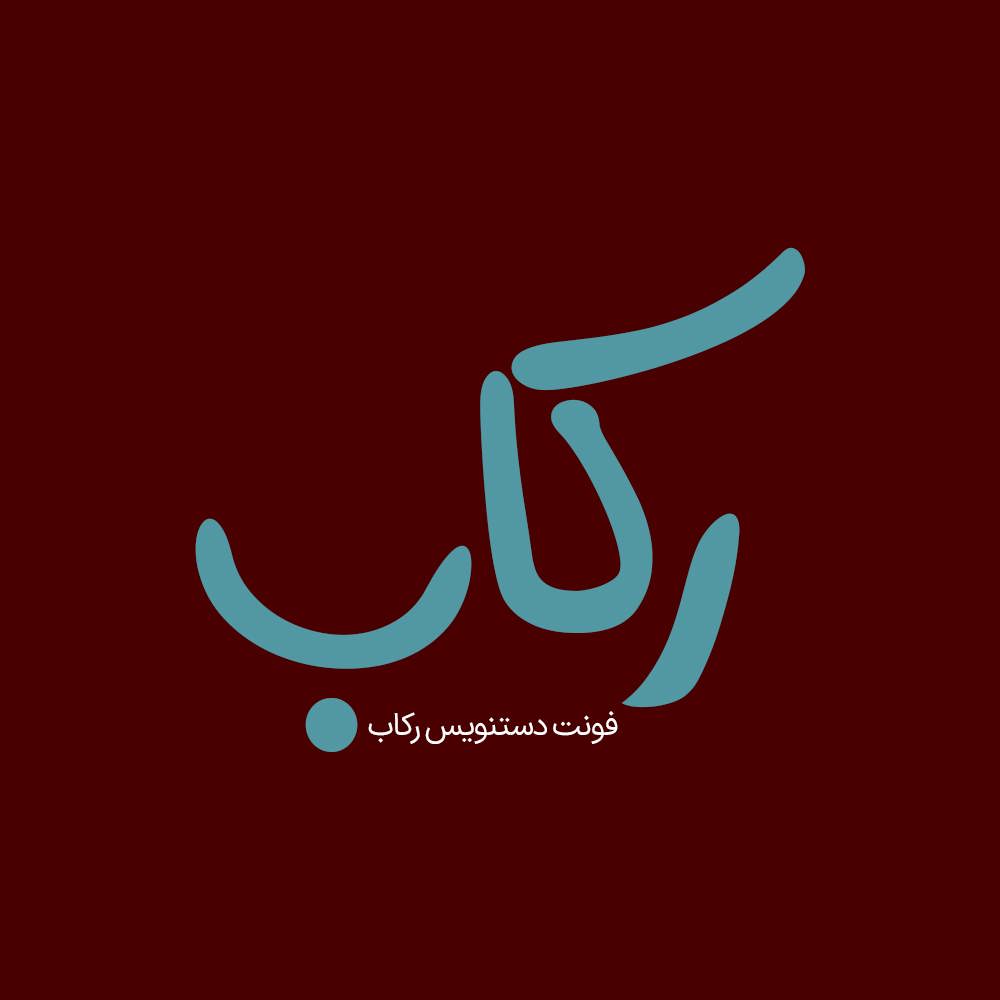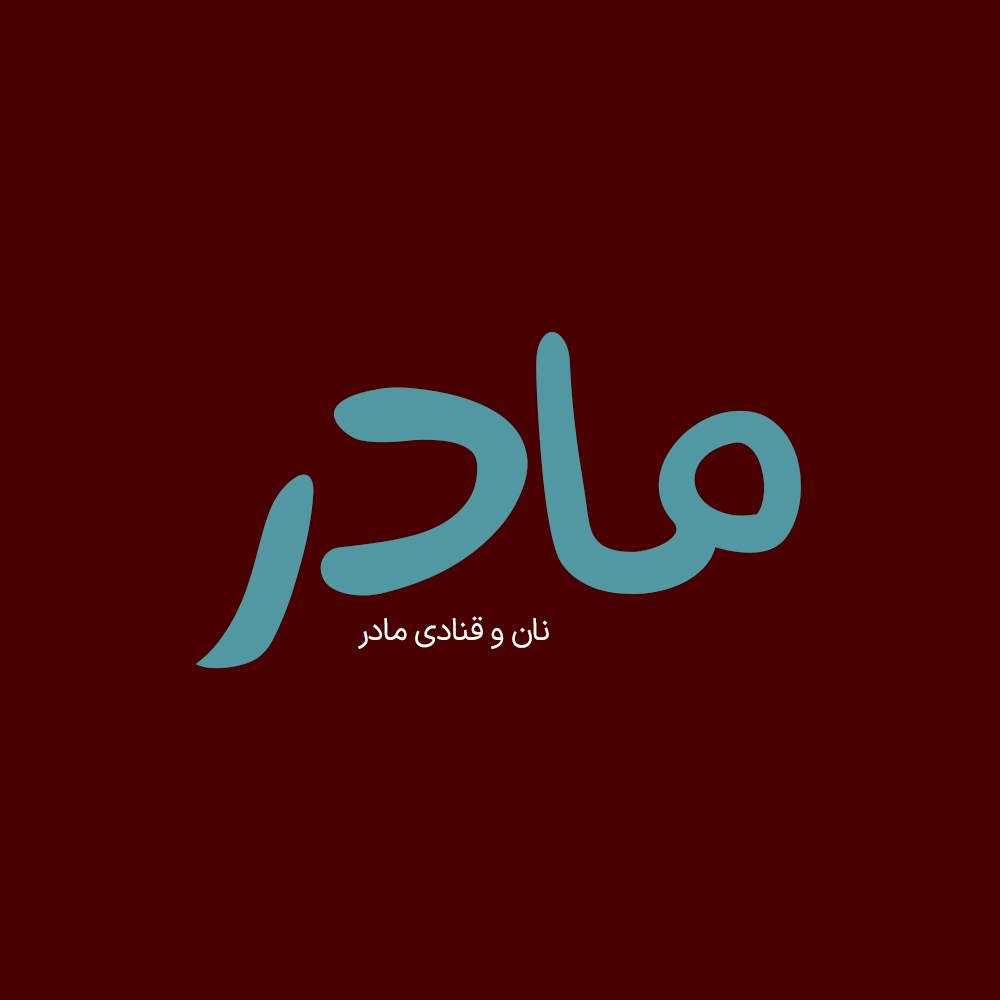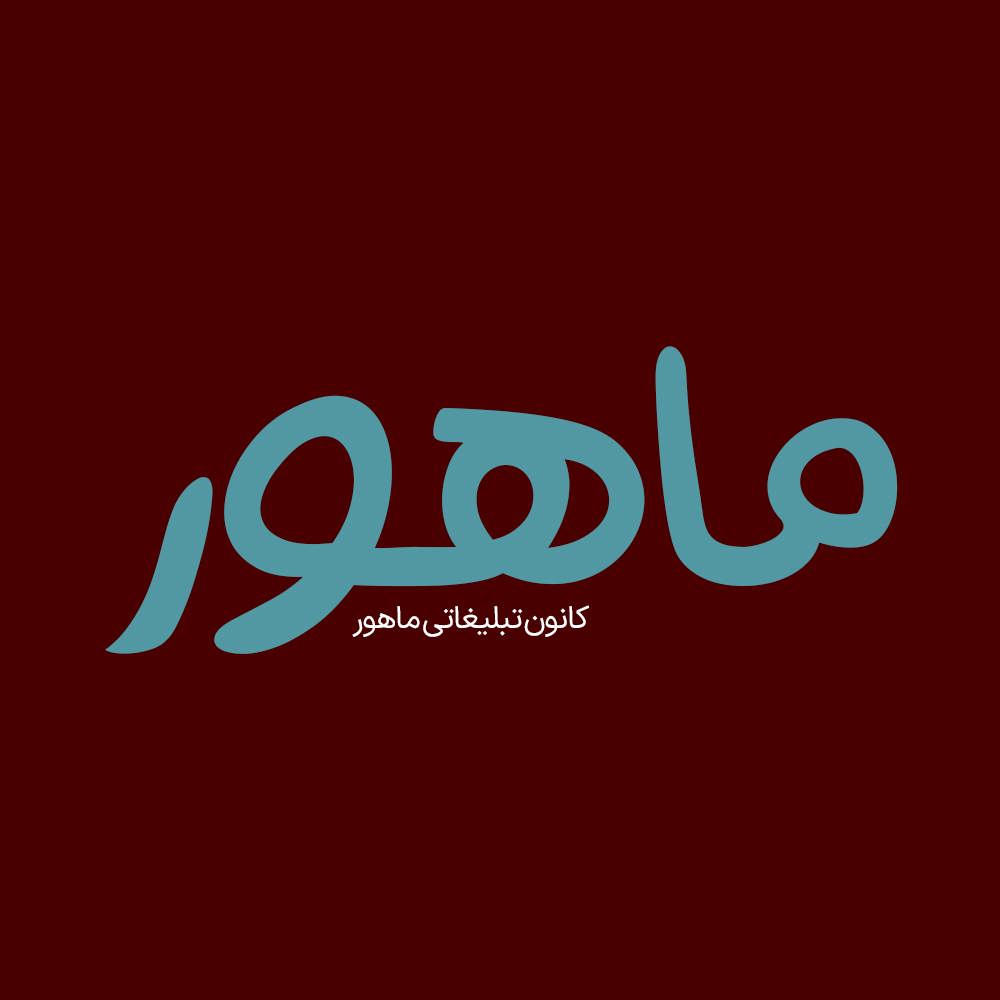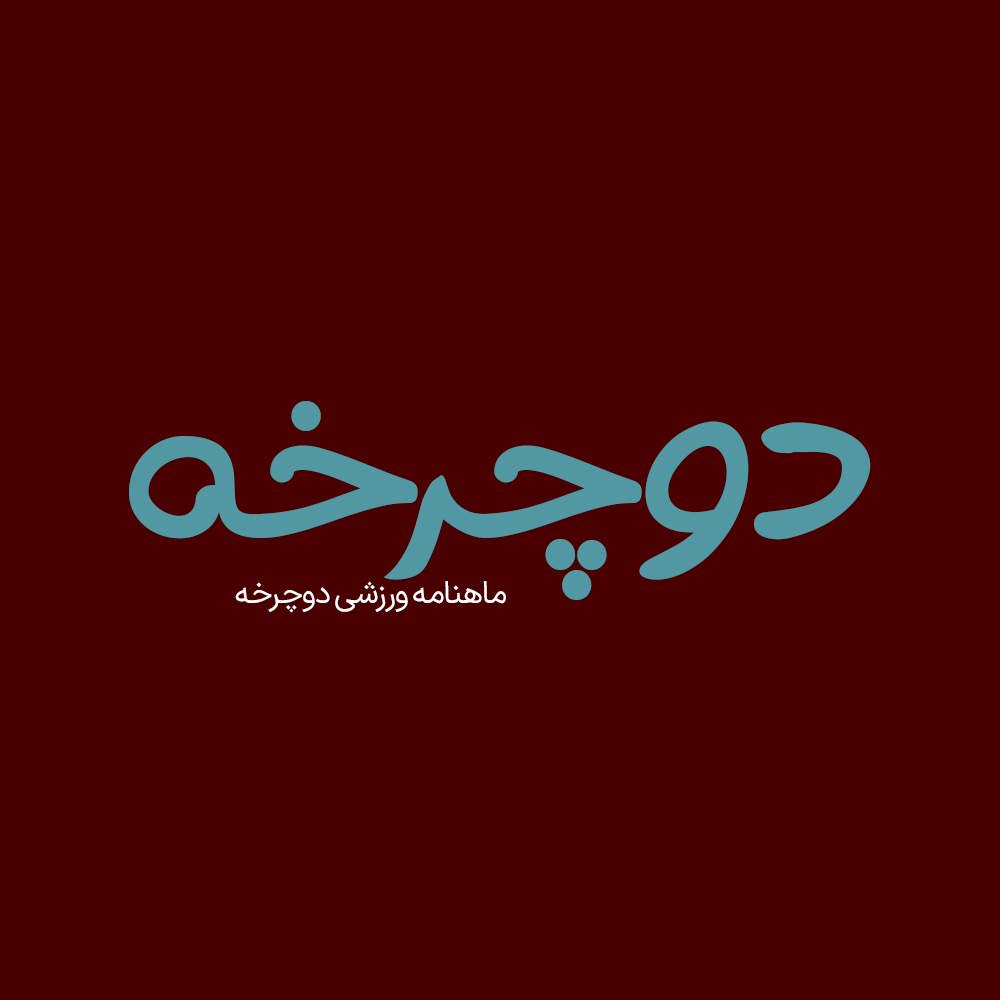
فونت فارسی رکاب Rekab Font
فونت دستنویس رکاب یک فونت بسیار زیبا و حرفه ای و متفاوت برای طراحی انواع امور گرافیکی به خصوص طراحی انواع لوگوتایپ و تایپوگرافی می باشد…
Rekab 1
فونت دستنویس رکاب یک فونت بسیار زیبا و حرفه ای و متفاوت برای طراحی انواع امور گرافیکی به خصوص طراحی انواع لوگوتایپ و تایپوگرافی می باشد شما با استفاده از فونت رکاب میتوانید لوگوتایپ و طراحی های زیبایی خلق کنید.
فونت دستنویس رکاب، بهترین فونت دستنویس در هر نرم افزاری می تواند مورد استفاده قرار گیرد اما پیشنهاد میکنیم برای تایپوگرافی بهتر در نرم افزار های گرافیکی (فتوشاپ،ایلاستریتور،کورل و…) استفاده کنید تا با کمی چینش و سفارشی سازی یک خروجی حرفه ای داشته باشید. در ادامه برای شما نمونه تایپ های این محصول حرفه ای رو آماده کردیم که میتونید مشاهده کنید.
• مناسب طراحی بسته بندی ها و چاپ
• فونت ویژه تبلیغات محیطی
• فونت طراحی کاور اینستاگرام
• فونت حرفه ای برای تولید محتوا
• فونت فارسی طراحی وبسایت
• فونت طراحی لوگو تایپ فارسی
• مناسب استفاده در تابلو های چلنیوم و طراحی حروف
پیشنمایش و نمونه تایپ های فونت رکاب
Rekab 2
Rekab 3
Rekab 4
Rekab 5